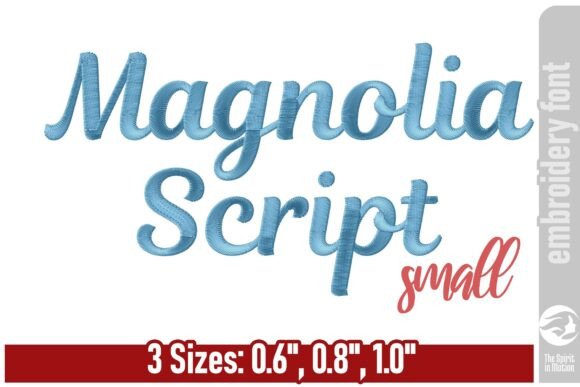
Magnolia Script Embroidery Font - Small
Việc tìm kiếm các thành phần thiết kế phù hợp có thể là một thách thức, nhưng Magnolia Script Embroidery Font - Small cung cấp một bộ sưu tập đặc biệt giúp nâng tầm công việc của bạn ngay lập tức.
Được chế tác với độ chính xác cao, Magnolia Script Embroidery Font - Small cung cấp các vector sạch, kiểu chữ mượt mà và giấy phép thương mại để bạn yên tâm.
Cho dù bạn đang tạo sản phẩm POD (In theo yêu cầu), thiệp mời đám cưới hay đồ họa mạng xã hội, Magnolia Script Embroidery Font - Small đều là một sự lựa chọn lý tưởng.